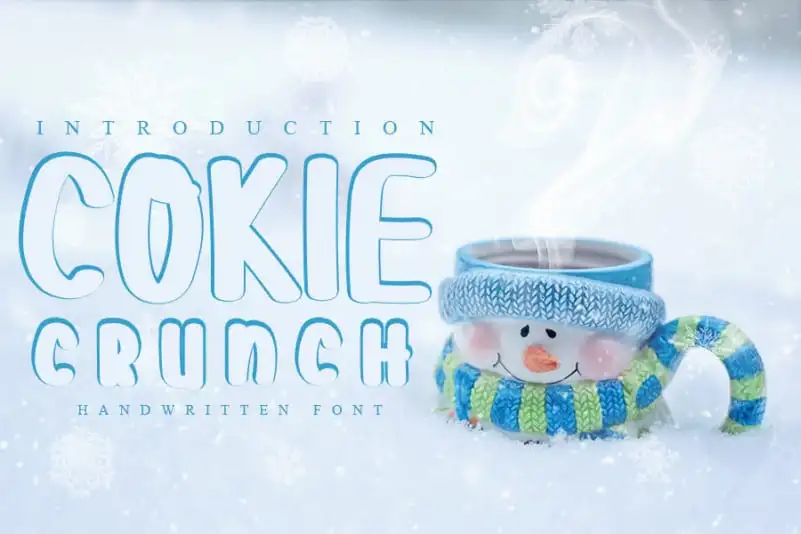
Cokie Crunch Display Font – Download Grátis
A fonte Cokie Crunch Display é uma escolha ideal para criar designs frescos e contemporâneos. Este tipo de letra é inspirado na escrita manuscrita, mantendo assim sua elegância clássica dos traços do calligrafista. No entanto, também reflete a sensação atualizada e cheia de vida que tanto os criativos quanto designers buscam em suas produções. Esta fonte tem uma versatilidade impressionante, fazendo-a perfeitamente adequada para uma variedade de ideias artísticas. Ela é ótima para aplicar em tudo: desde assinaturas e títulos até papelarias. Perfeita para aqueles que buscam um equilíbrio entre a clareza das fontes modernas e o charme do estilo pessoal da escrita manuscrita. Cokie Crunch Display é perfeito para quem valoriza a criatividade, busca uma mistura de tradição com atualidade no design e quer adicionar um toque especial aos seus projetos.